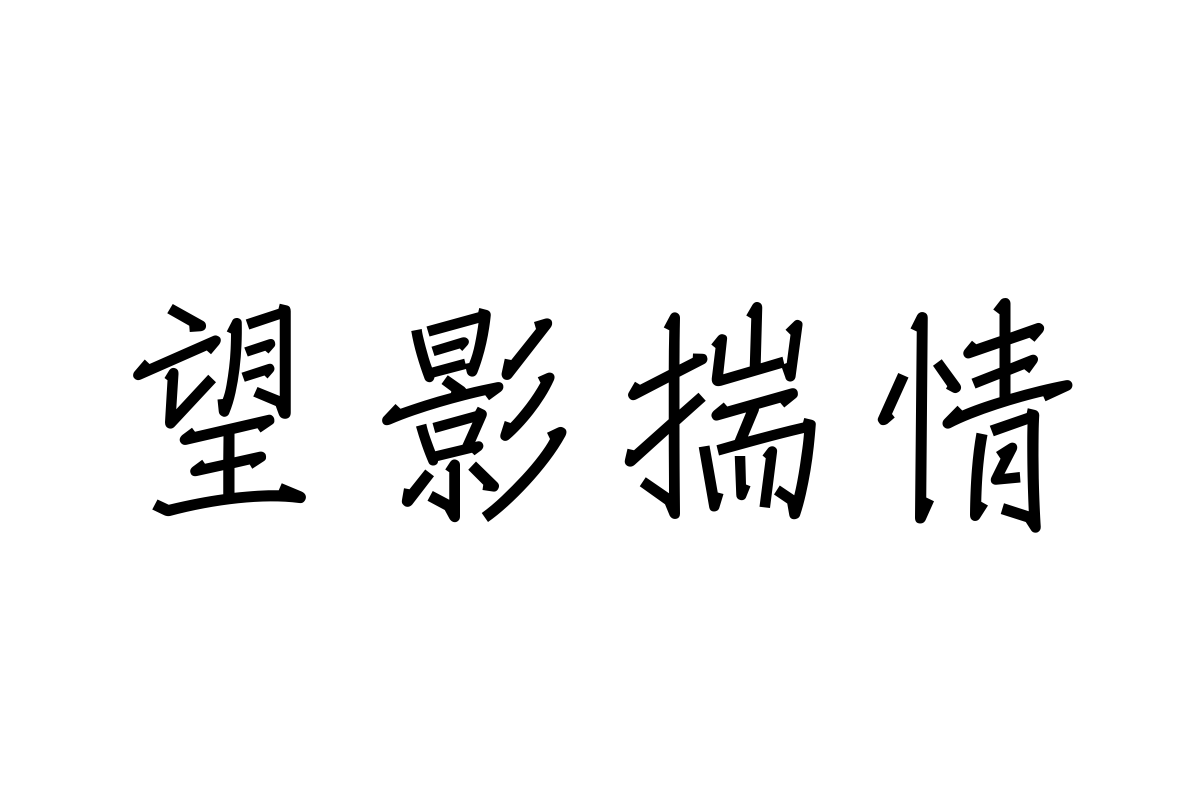
**汉仪洛神行35繁是一款具有现代感的字体,取意于赵孟頫行书《洛神赋》卷**。该字体结合了现代等线的笔画设计,保留了行楷的流畅潇洒,并尝试减弱其古旧气息。
汉仪洛神行35繁字体的设计灵感来源于赵孟頫行书《洛神赋》卷。这种字体在字形结构上追求一种“竦轻躯以鹤立,若将飞而未翔”的意境,旨在通过现代等线笔画的设计,既保留行楷的流畅潇洒,又不失其艺术韵味。这种设计使得汉仪洛神行35繁不仅适合用于正式的文本排版,也适合用于需要表现古典美和现代感相结合的场景,如书籍、杂志、网站等。
总的来说,汉仪洛神行35繁字体以其独特的设计和广泛的应用潜力,成为了现代中文排版中不可或缺的一部分。